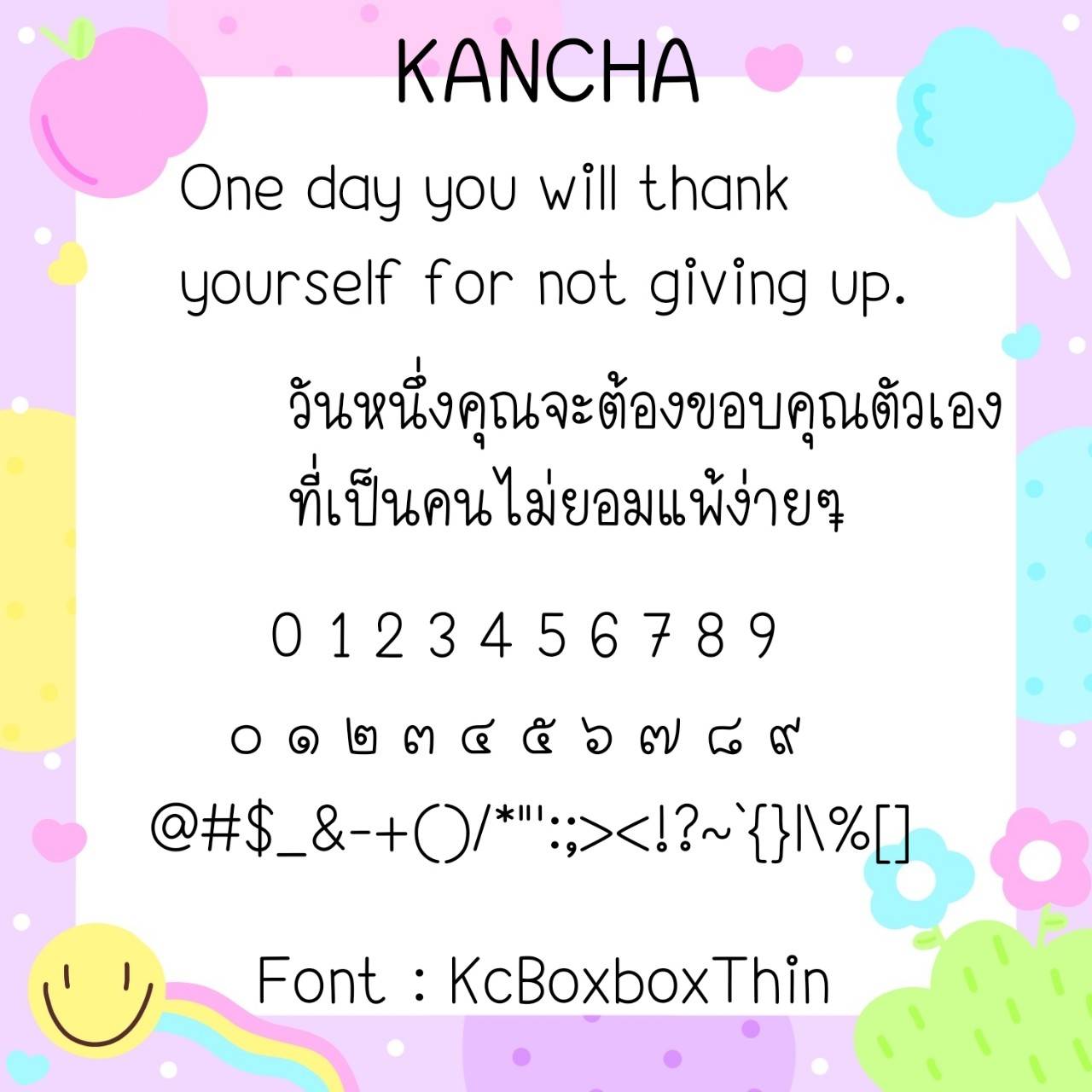
Font KcBoxbox
ชื่อสินค้า : Font KcBoxbox 💙
🔸ฟอนต์อ่านง่าย กึ่งแนววัยรุ่น ดูสบายตา มีอิโมจิเจ้าหมาโดก้าแทนตัวเลขไทยให้ในชุดด้วยค่ะ 🥰💙
🔹easy to read font Semi-teenager style, comfortable to the eye, with Doca dog emojis instead of Thai numbers in the set as well.🥰💙